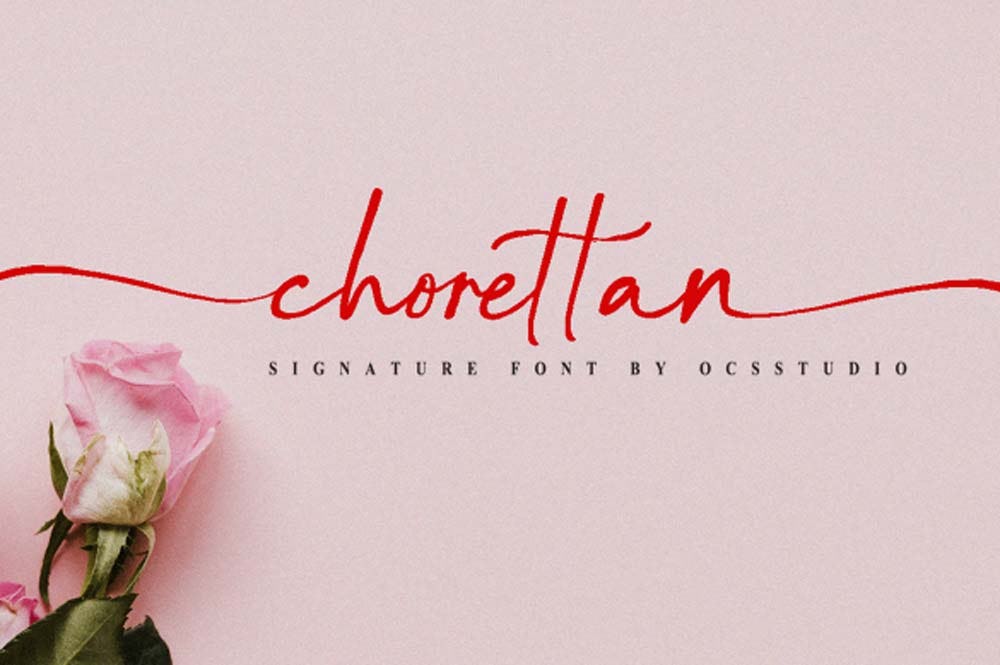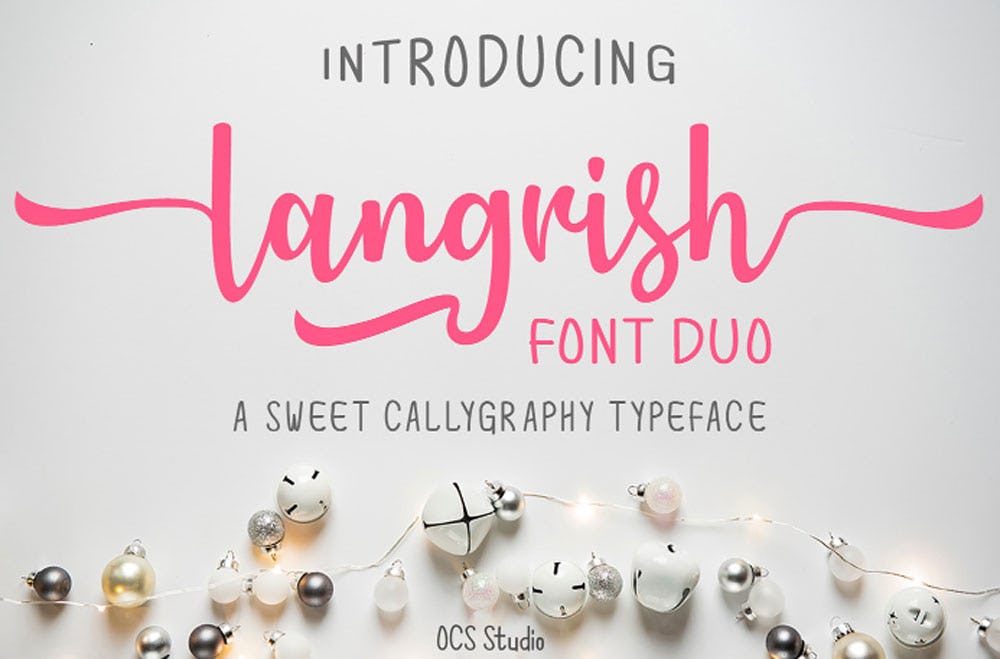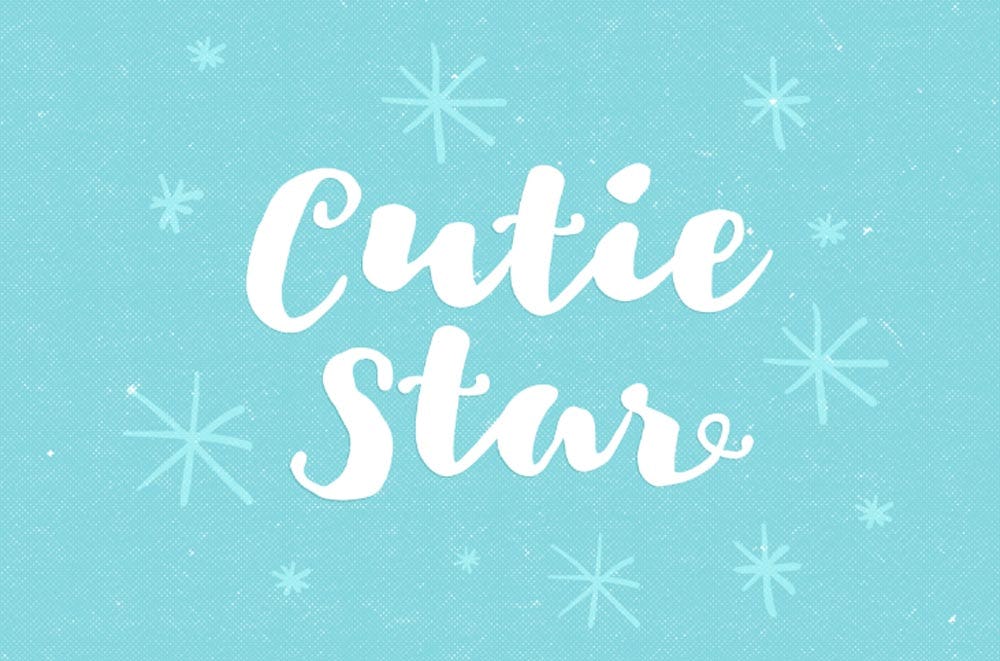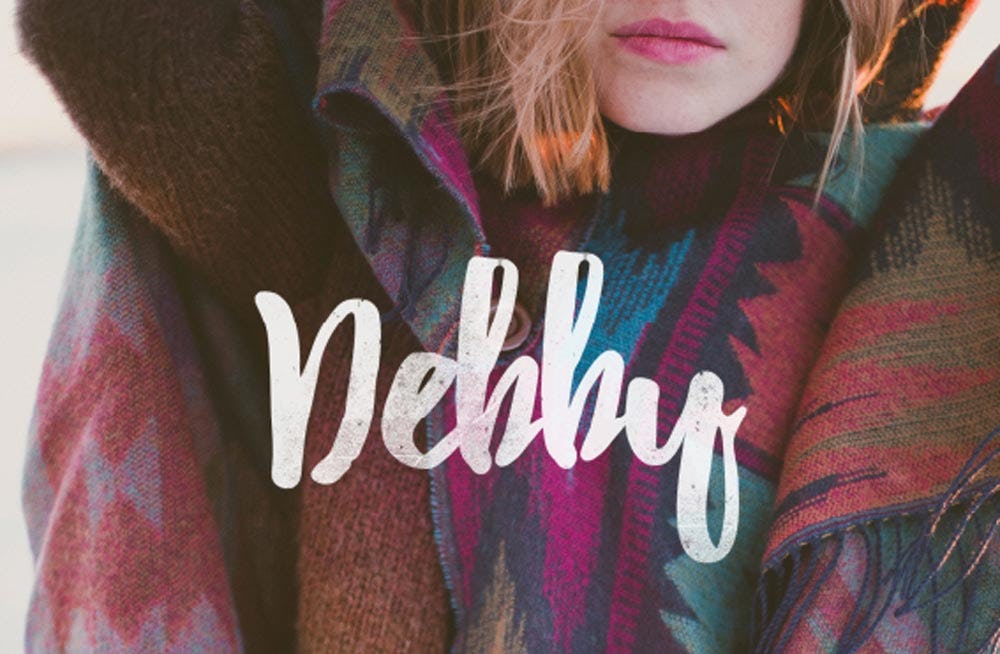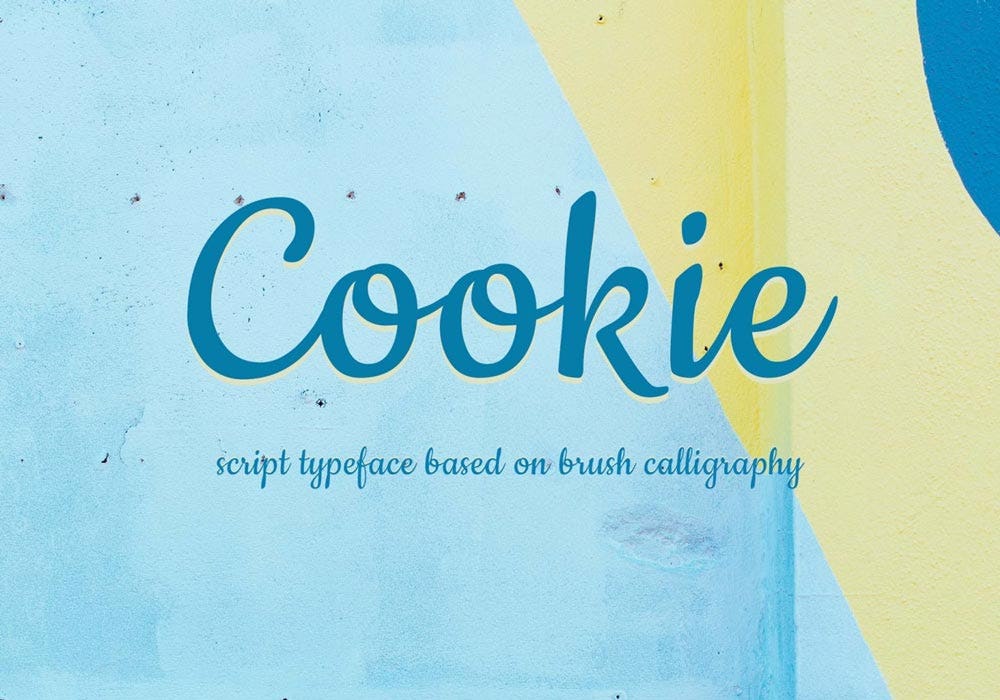
Las lettering fonts son una de las tendencias más populares en tipografía que darán que hablar en el 2022. Pero ¿qué es lo que nos atrae tanto de las lettering fonts? ¿Por qué siguen siendo las favoritas de muchos?
Esto se debe, principalmente, a su carácter personalizado. El lettering busca generar una tipografía particular, espontánea, con elementos o formas que las tipografías de imprenta o de uso en diseño digital no pueden ofrecer. Por ejemplo: orlas grandes, trazos que se entrecruzan o envuelven a las palabras, etc.
De ahí su carácter exclusivo, manual y personal. Por lo general, las letras dibujadas a mano están basadas en alguna tipografía existente, aunque lo ideal es que aporten alguna forma o elemento nuevo, ya sea en el trazo o en ciertos caracteres.
Hoy en día existe una gran variedad de tipografías inspiradas en la escritura a mano. En una entrevista realizada por el portal web ABC de Sevilla, José Gil, calígrafo experto en lettering, menciona que la escritura manual era un arte perdido y hoy ha resucitado debido a la nostalgia por las cosas hechas a mano.
Sabemos que buscar entre las miles de opciones que hay en la web puede ser una tarea que podría tomarte horas. Pero no te preocupes, nosotros hemos realizado esta parte pesada y en este artículo te traemos una selección de las mejores lettering fonts que no puedes dejar pasar.
Así que, ¡manos a la obra y empieza a usarlas!
1. Leira Font
Es una fuente lettering mayúscula dibujada a mano, por lo que le dará un toque personal a tus diseños. Es ideal para crear identidades, logotipos, carteles, tarjetas y diseño de empaques. Incluye números y símbolos.
2. Romello Font
Es una fuente lettering creada por Ardyana Types. Se caracteriza por ser elegante, fácil de leer, recordar y usar. Es la opción perfecta para usar en diseños de carteles, firmas, logotipos, citas, portadas de álbumes, tarjetas de visita, diseños de productos y muchos otros proyectos de diseño. Sin duda, una de las lettering fonts pensada para que tus diseños luzcan encantadores y divertidos.
3. Lovely Font
Esta fuente de lettering es ideal para diseños de citas, tarjetas y productos, entre otros. Además, cuenta con dos fuentes diferentes. Una, sin cola al inicio de la palabra y otra con cola. Para usar esta última, se necesita cambiar la fuente familiar a "Lovely Swashes Tail".
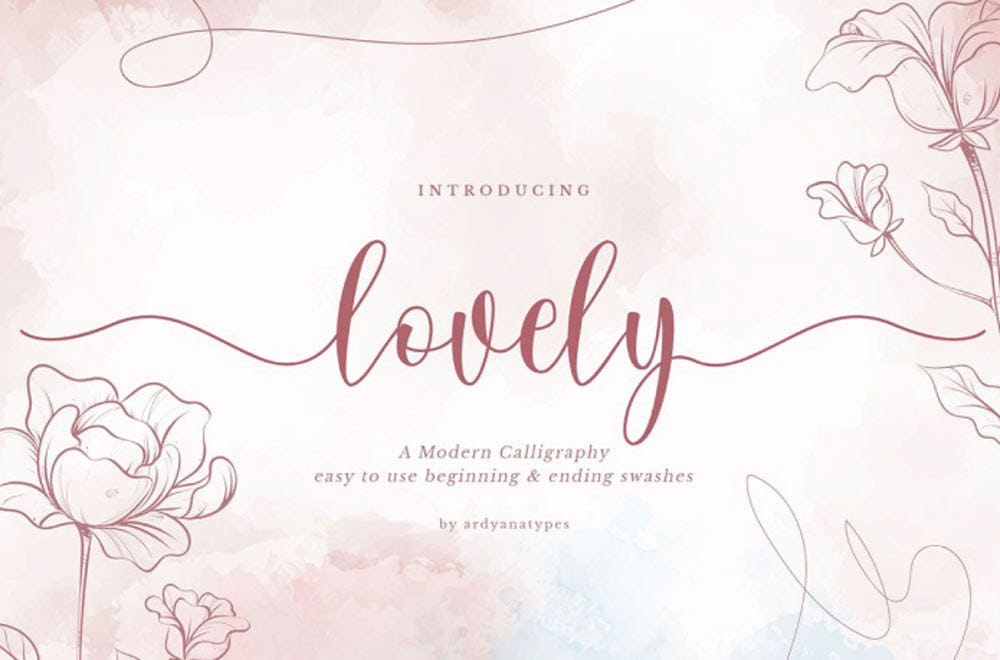
4. Naibacarte Font
Es una fuente de caligrafía moderna, inspirada en el poder del amor y la pasión. Sus creadores (Nirmana Visual) recomiendan usarla en marcas, proyectos de bodas, logotipos, citas, etc.
5. Streetwear Font
Se trata de una de las lettering fonts que te recuerda a la moda y el deporte de los años 60 y 70. Es una fuente de lettering elegante y divertida, inspirada en el estilo retro; ideal para el diseño de empaques, camisetas, logotipos, carteles, etc. Además, te permite acceder a los caracteres alternativos a través de programas OpenType, como Adobe Illustrator e InDesign.
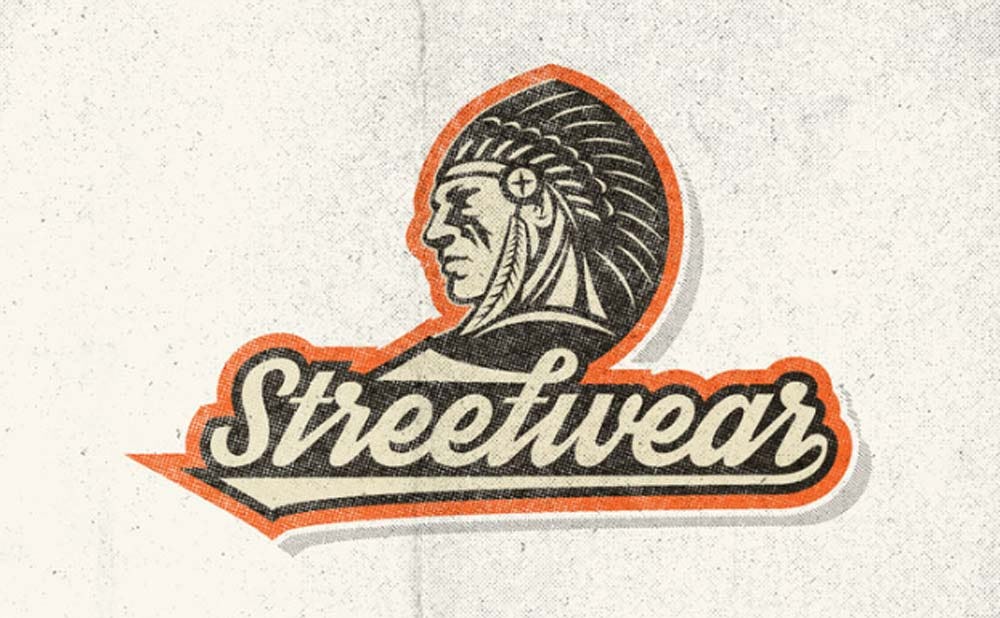
6. Tahu Font
Fuente de escritura moderna, limpia y profesional. Puedes usarla para anuncios digitales, logotipos o branding. Esta fuente de lettering tiene letras mayúsculas, minúsculas, números, signos de puntuación y es multilingüe.
7. Roomfer Font
Esta lettering font en pincel tiene un estilo de escritura a mano y en negrita. Su uso es para diseños que tienen un estilo relajado, juvenil y fresco. Puedes usarla como texto de título, logotipo, concepto de diseño de dibujo a mano, nombre de invitaciones de boda, etc.
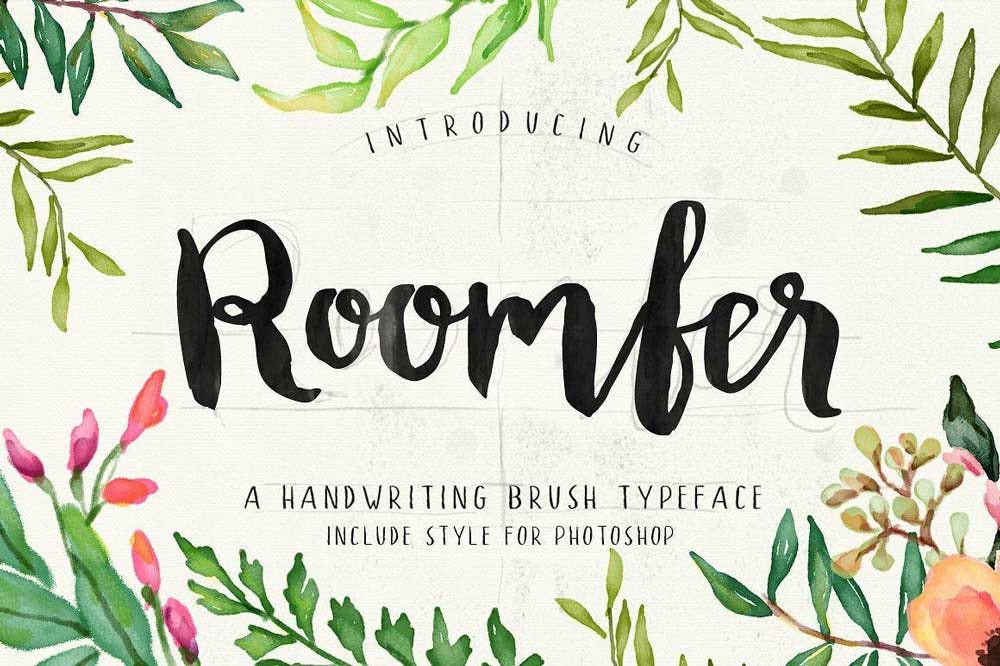
8. Mooglonk Font
Las fuentes de escritura usan un estilo clásico elegante de línea única y, justamente, Mooglonk serif usa un estilo vintage y firme. Incluye la fuente de escritura a mano y serif.
Ambas fuentes de lettering incluyen letras mayúsculas y minúsculas, multilingüe, números, moneda y puntuación. De hecho, tiene vectores y pinceles para Photoshop.
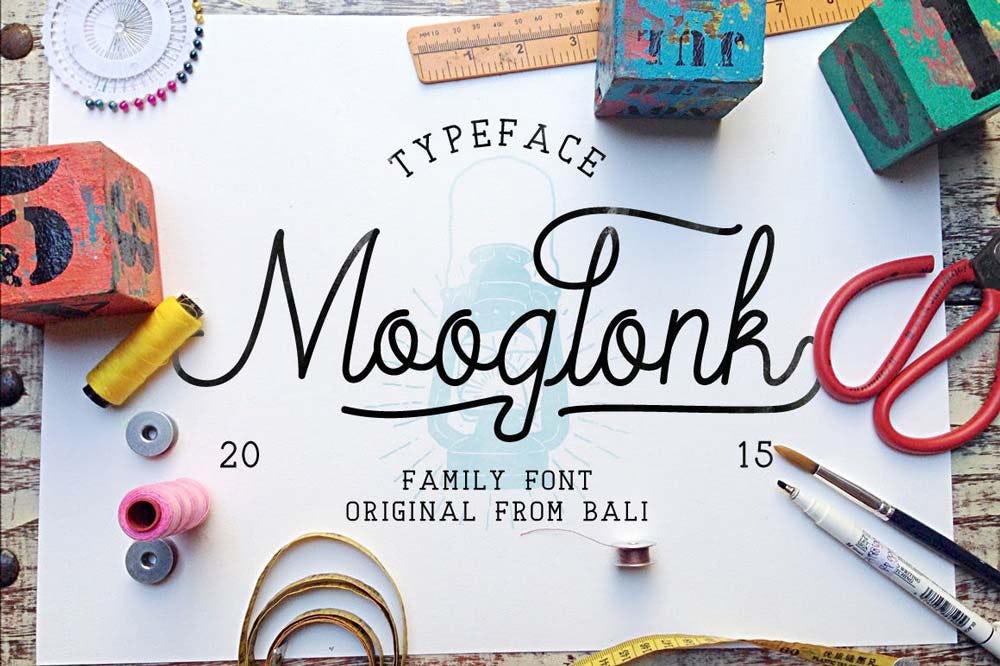
9. Moonbrigth Font
Esta fuente de lettering es perfecta para titulares o decoración. Moonbrigth, de Brittney Murphy, incluye mayúsculas, minúsculas, números, símbolos, elementos de puntuación y soporte para idiomas extranjeros basados en el latín.
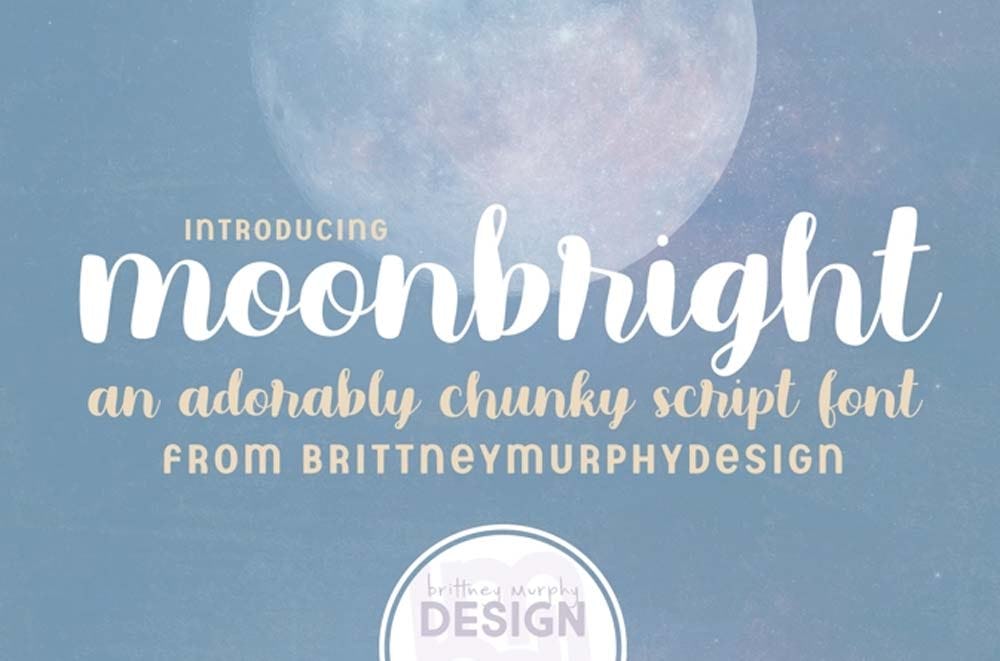
10. Chorettan Font
Una lettering font elegante y perfecta para usarla en invitaciones de boda, imágenes para redes sociales, logotipos, etc. Las fuentes Chorettan están equipadas con dos fuentes regulares y fuentes en cursiva para que puedas elegir entre las dos.
Estamos seguros que estas lettering fonts te ayudarán a desarrollar cualquier proyecto personal o comercial. Eso sí, es importante que tomes en consideración la licencia de uso y seas respetuoso con la autoría de cada fuente.